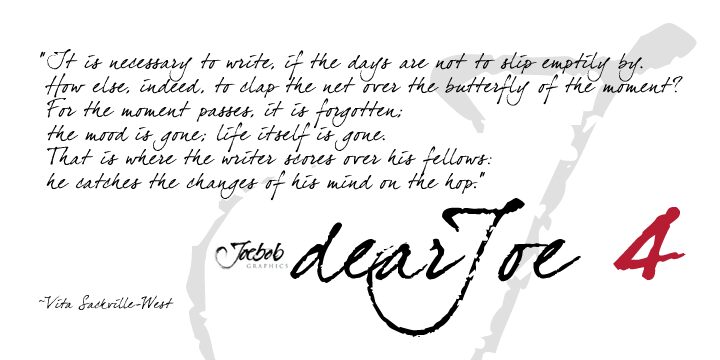
dearJoe four od J O E B O B graphics to darmowy font odręczny, który oddaje surowy, pełen atramentu charakter prawdziwego podpisu, nie tracąc przy tym na czytelności. Pociągnięcia wydają się być wydrapane i przeciągnięte po stronie, z nieregularnym naciskiem i ziarnistymi krawędziami, dzięki czemu projekty cyfrowe wyglądają, jakby zostały wykonane ulubionym piórem na fakturowanym papierze. Luźny rytm nadaje całości ludzki, autentyczny charakter, a odstępy pozostają czytelne nawet przy mniejszych rozmiarach.
Używając dearJoe four, uzyskasz ten niechlujny, osobisty efekt odręcznego pisma, którego stworzenie zazwyczaj zajmuje godziny. Ten darmowy font świetnie sprawdza się w podpisach marek, etykietach, okładkach książek, plakatach, grafikach do mediów społecznościowych i ręcznie robionych zaproszeniach. Wygląda najlepiej jako nagłówek lub nazwa, zestawiony z prostym krojem bezszeryfowym w tekście głównym, co zapewnia zrównoważony i nowoczesny wygląd.
To jest wersja próbna fontu odręcznego dearJoe IV. Niektóre pary kerningowe wymagają jeszcze korekty.